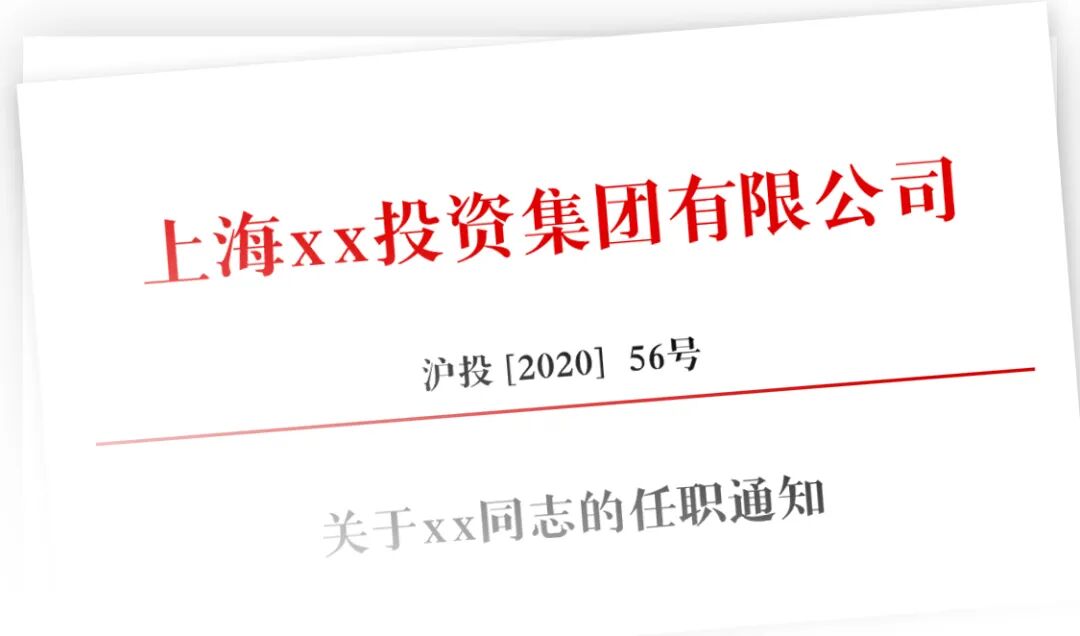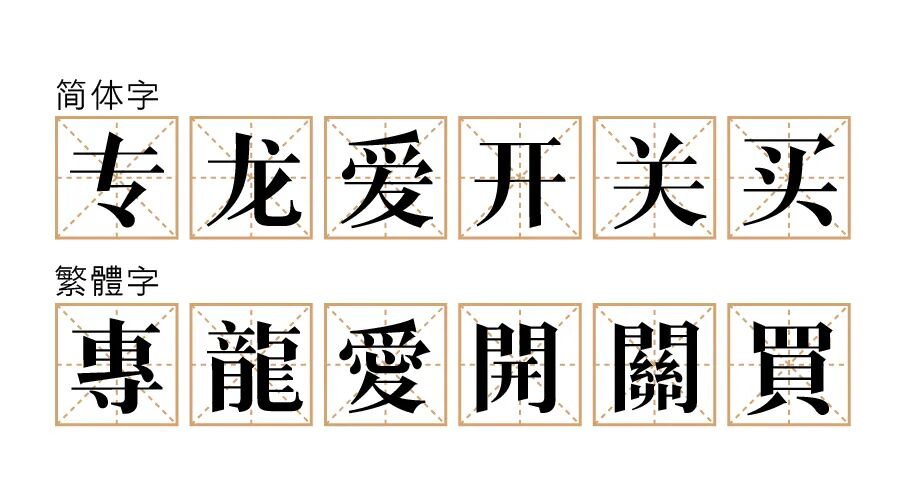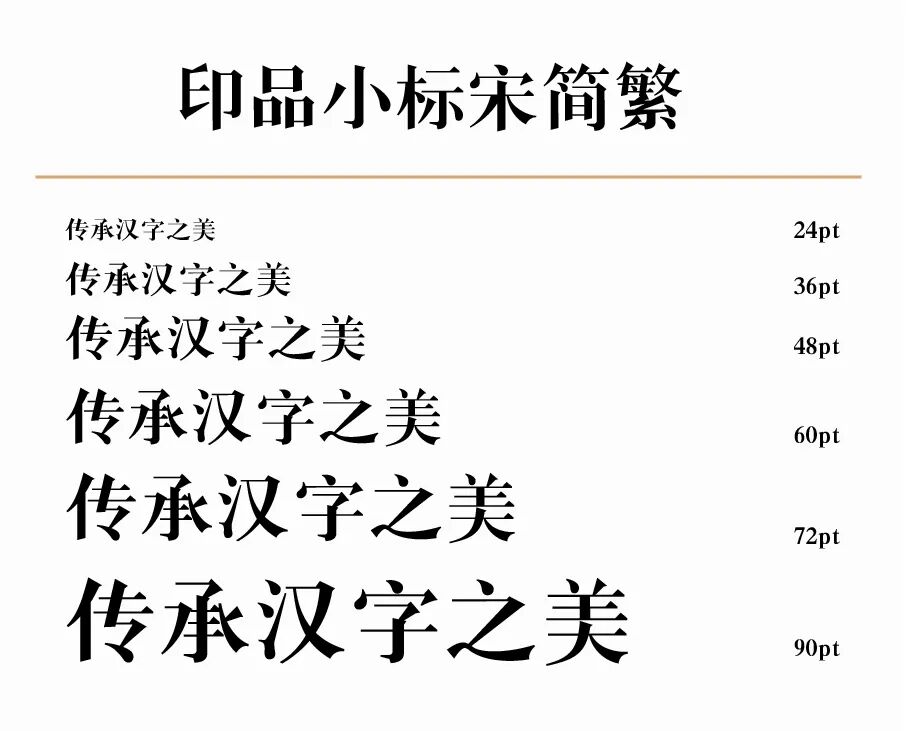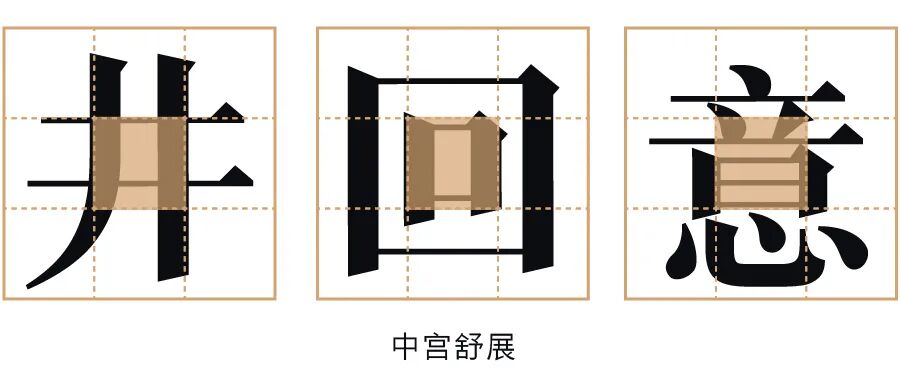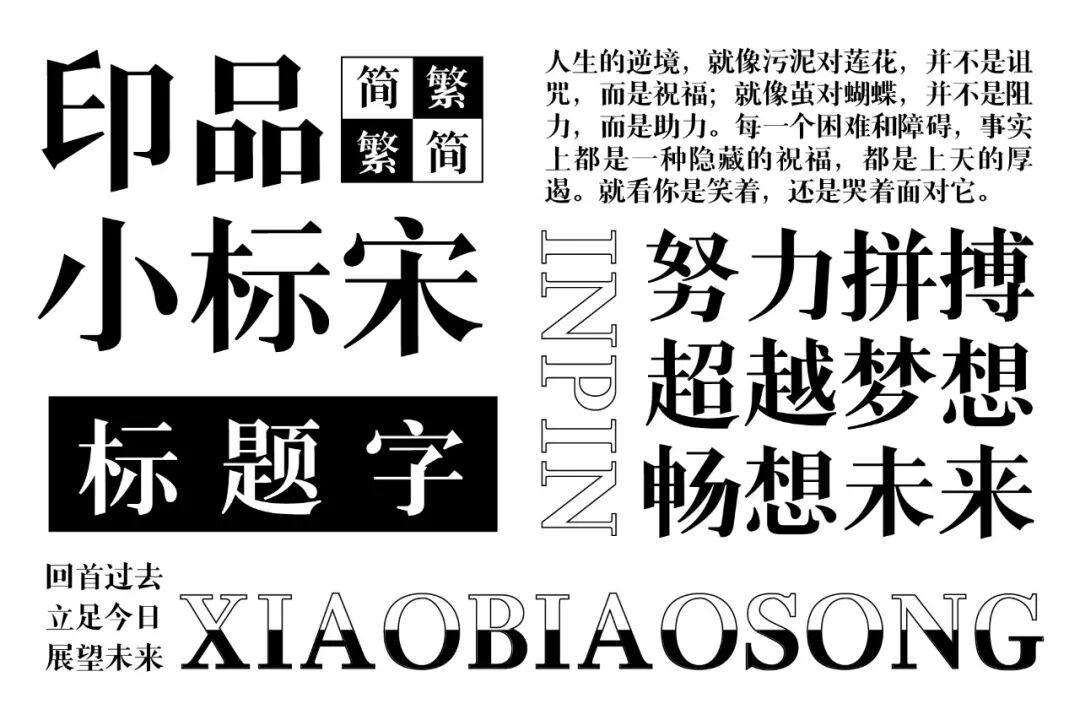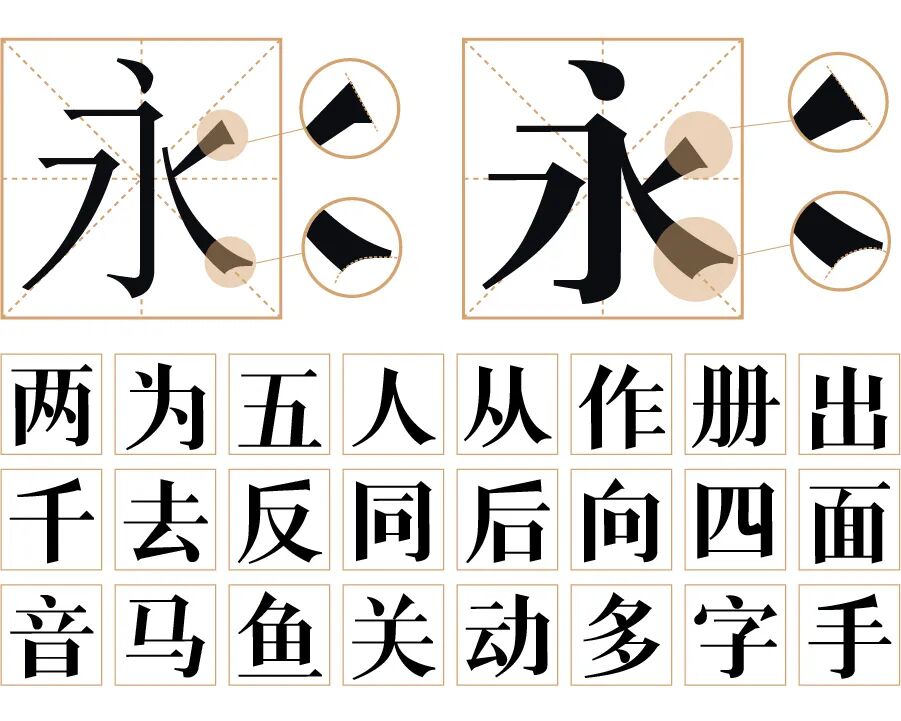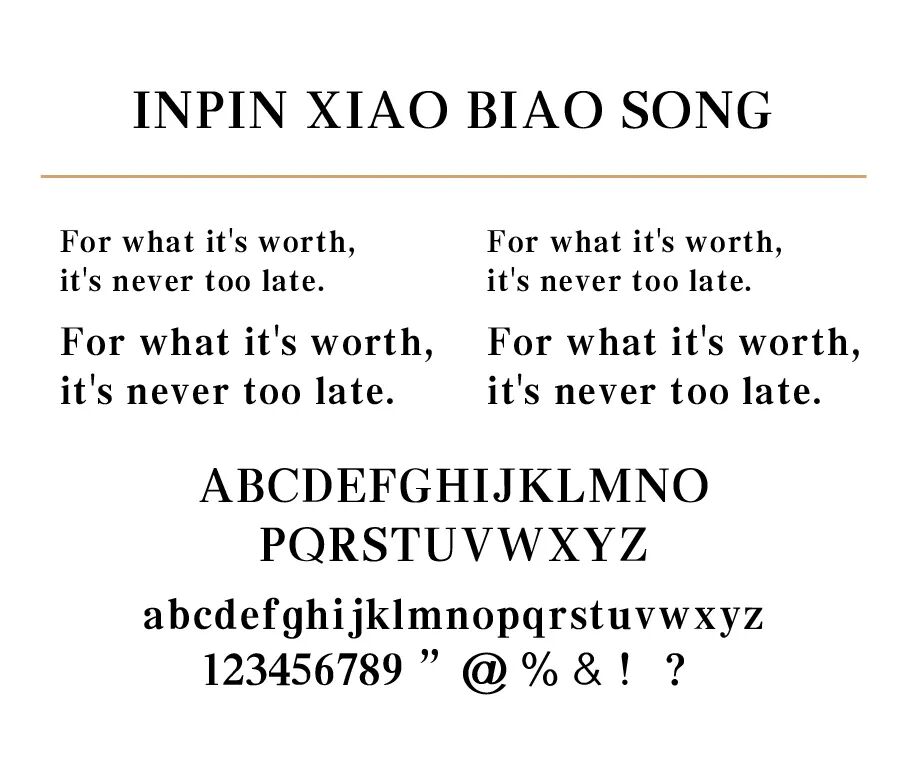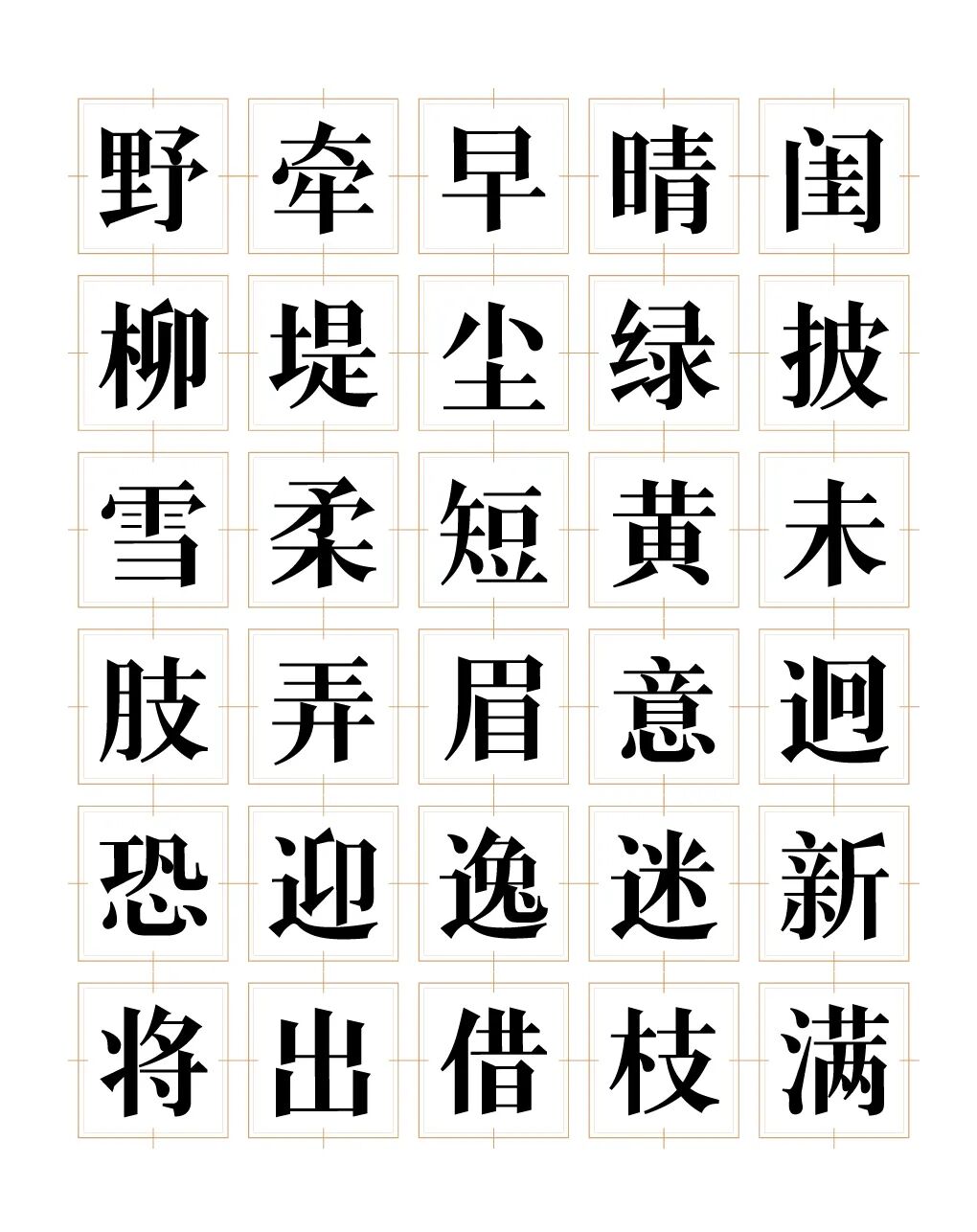
小 标宋 长这样。
印品小标宋简繁为了满足党政机关公文用字体的高要求而专门精修的字库产品,字体美观规范、清晰易读,完全保证电子公文共享交流时统一、准确、原版的完美显示。
笔画横细竖粗,厚重而刚劲,有重力感。字形古典端庄,雍容雄秀,结构严谨而宽舒、圆满、匀称。 结构端正,显得比较硬朗,中宫比较舒展;笔画横轻竖重,横线尾呈三角状,点、撇、捺、钩等笔画有尖端,字形端正、刚劲有力。